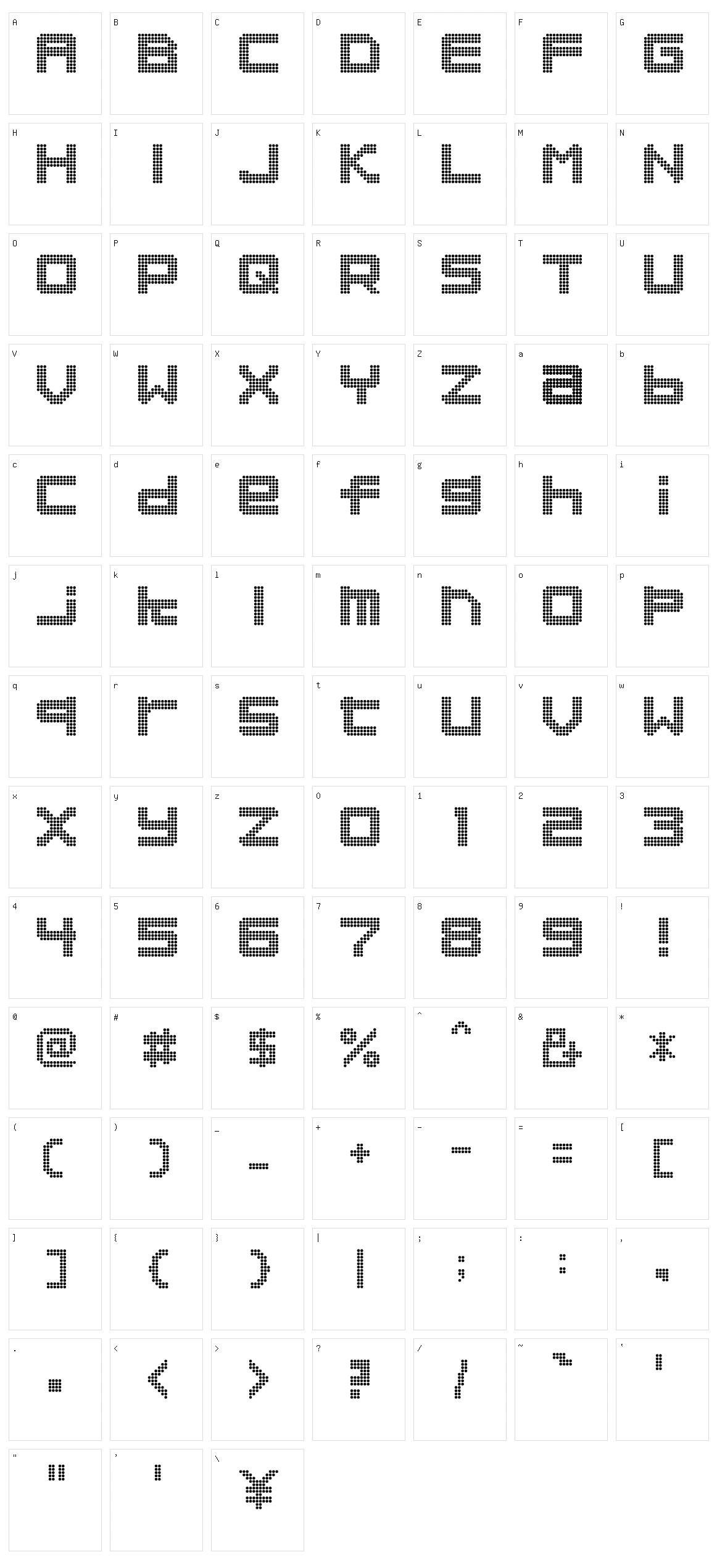
Orandakan Kana
šƒIƒ‰ƒ“ƒ_ƒJƒ“ƒJƒi
Orandakan Kana Font
¡‚±‚̃tƒHƒ“ƒg‚ɂ‚¢‚Ä
ƒIƒ‰ƒ“ƒ_‚̃fƒUƒCƒi[AƒEƒBƒ€EƒNƒƒEƒGƒ‹iWim Crouwelj‚ª1970”N‚Ì‘åã–œ”ŽƒIƒ‰ƒ“ƒ_ŠÙ‚Ì‚½‚߂ɃfƒUƒCƒ“‚µ‚½uƒIƒ‰ƒ“ƒ_v‚̃ƒS‚ð–|ˆÄ‚µ‚½ƒtƒHƒ“ƒg‚Å‚·BƒIƒŠƒWƒiƒ‹‚́uƒIvuƒ‰vuƒ“vuƒ_v‚Ì4•¶Žš‚µ‚©‚È‚¢‚̂ŁAŽc‚è‚Í‘z‘œ‚ōì‚è‚Ü‚µ‚½BŠ¿ŽšA‚Ђ炪‚ȁA”¼ŠpƒJƒi‚Í“ü‚Á‚Ä‚¢‚Ü‚¹‚ñiì‚é—\’è‚Í‚ ‚è‚Ü‚¹‚ñjB
“™•‚̂悤‚ÉŒ©‚¦‚Ü‚·‚ªƒvƒƒ|[ƒVƒ‡ƒiƒ‹‚Å‚·B‚©‚Æ‚¢‚Á‚ÄŽšŠÔ‚̓†ƒ‹ƒ†ƒ‹‚Å‚·BŠeŽ©‚Ńcƒ‚Ä‚­‚¾‚³‚¢B
E‚Ђ炪‚ȂƃJƒ^ƒJƒi‚̐´‰¹‚Í“ü‚ê‚Ä‚é•¶Žš‚ª­‚µ‚¾‚¯ˆá‚¢‚Ü‚·Bu‚ ^ƒAvu‚©^ƒJvu‚­^ƒNvu‚¹^ƒZvu‚́^ƒnvu‚ց^ƒwvu‚ف^ƒzvu‚݁^ƒ~vu‚߁^ƒv‚̈Ⴂ‚͊ԈႢ‚ł͂Ȃ­AƒIƒ‹ƒ^ƒlƒCƒg‘Ì‚¾‚ÆŽv‚Á‚Ä‚­‚¾‚³‚¢B
E‘÷‰¹^”¼‘÷‰¹‚̏ˆ—‚̓IƒŠƒWƒiƒ‹‚̏ˆ—‚𑸏d‚µ‚Ä‚¢‚Ü‚·B‚»‚Ì‚½‚߁AƒJƒ^ƒJƒi‚Ì‘÷‰¹ŠÖŒW‚Ì•¶Žš‚ÍŽš•‚ª‰¡‚É’·‚­‚È‚Á‚Ä‚¢‚Ü‚·B‚Ђ炪‚Ȃ̑÷‰¹ŠÖŒW‚͐H‚¢ž‚ݏˆ—‚É‚µ‚Ä‚ ‚è‚Ü‚·BƒJƒ^ƒJƒi‚͉¡‘‚«—pA‚Ђ炪‚Ȃ͏c‘‚«—p‚Æ‚µ‚āAŽg‚¢•ª‚¯‚Ä‚­‚¾‚³‚¢B
EŒ³‚ªƒƒS‚Ȃ̂ŁAƒ^ƒCƒgƒ‹‚〈o‚µ‚ȂǑ傫‚߂Ɏg‚¤‚±‚Æ‚ª‘O’ñ‚Å‚·B¬‚³‚­Žg‚¤‚ƃhƒbƒg‚ªƒcƒu‚ê‚Ĉóü‚Å‚«‚È‚©‚Á‚½‚肵‚Ü‚·B‚¨‹C‚ð‚‚¯‚­‚¾‚³‚¢B